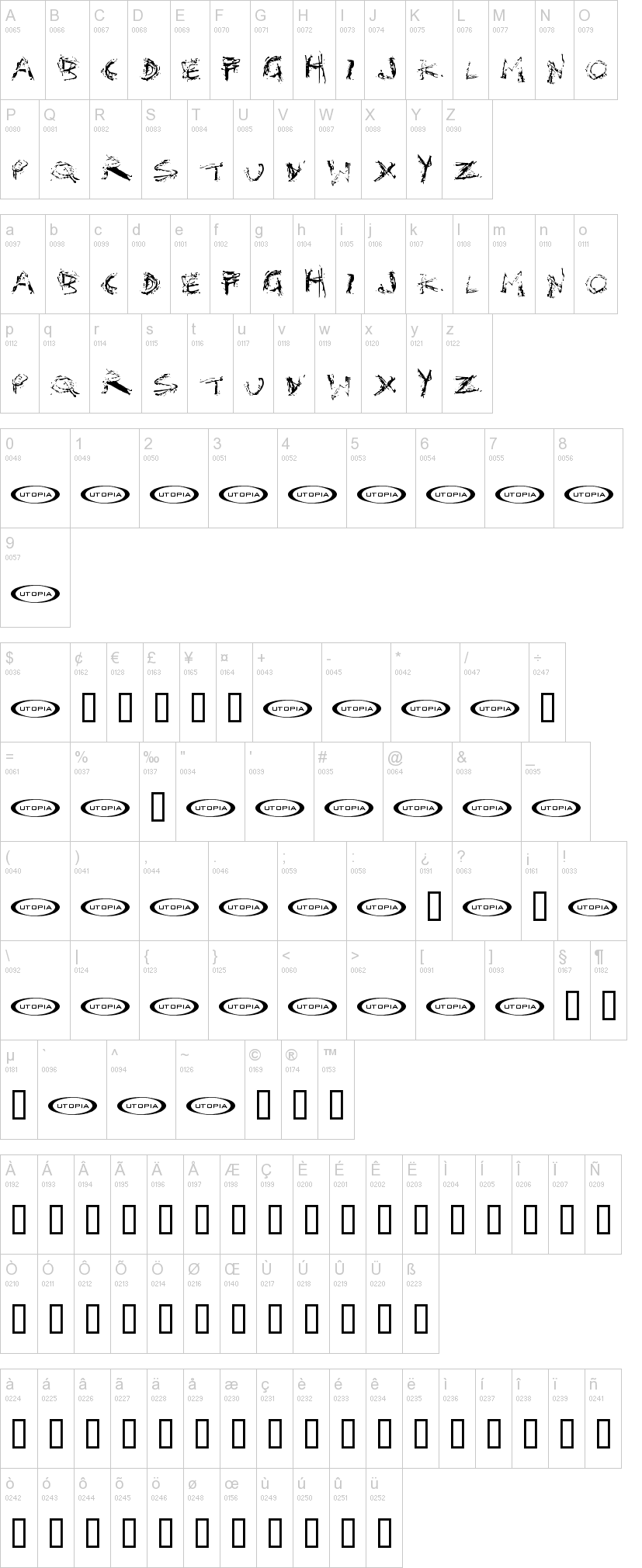
Distortia 是一种现代风格的字体,它的设计灵感来自于机器、科技、未来等元素。这种字体的特点是字符笔画的变形扭曲,给人一种科技感和未来感。Distortia 字体的设计师是来自英国的 Matt Lyon,他利用计算机生成的算法来制作这种字体,使得每个字符都具有独特的形态和线条。 Distortia 字体的使用范围很广,特别适合用于科技、游戏、电影、音乐等现代化领域中的品牌标志、广告宣传、海报设计等。在设计上,Distortia 字体可以与其他简单明了的字体进行搭配,增强品牌的辨识度和视觉冲击力。同时,这种字体的变形扭曲特点还可以为设计师带来更多的创作灵感和可能性。内容介绍
Distortia是一款非常不错的手写艺术字体,具有很好的视觉感,适合于文化类的宣传设计、商业类品牌的广告和产品包装设计以及个性化文字排版等较多场景。